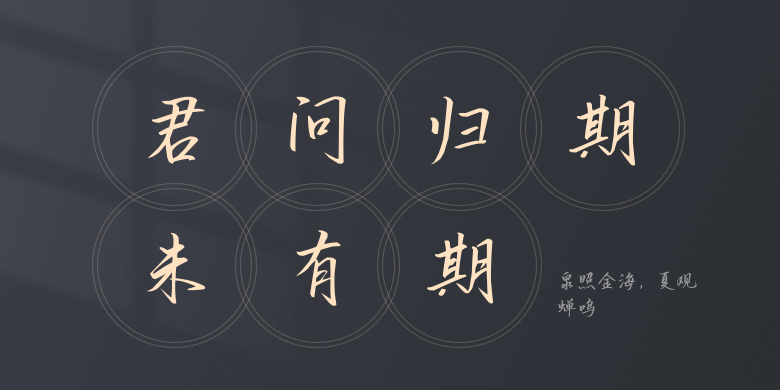
泉照金海,夏观蝉鸣
泉照金海,夏观蝉鸣,这款字体结构工整、笔画清晰,兼顾美观与易读性,适用于标题、正文、海报、包装、LOGO 等多种场景。字形优雅稳定,风格百搭耐看,适配日常排版与创意设计,让文字呈现更舒适、更具质感。泉照金海,夏观蝉鸣一笔一画,皆是细节,以均衡的比例、流畅的线条打造舒适视觉体验,字形端正大气,风格简约现代。无论是商业设计、品牌宣传还是日常排版,都能轻松驾驭,让文字更有格调与力量。泉照金海,夏观蝉鸣字体下载。